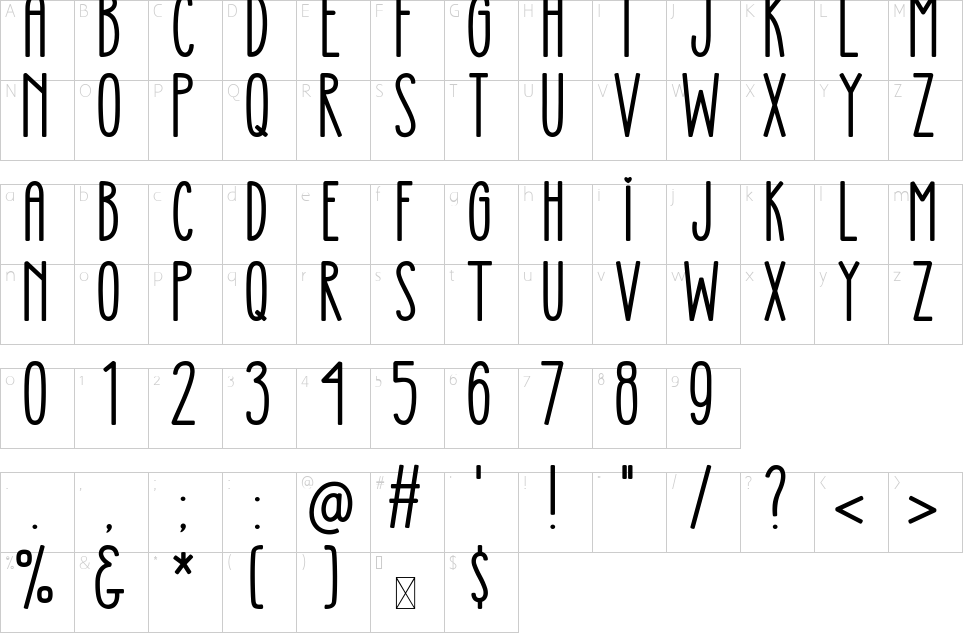
Descubra a delicadeza e o charme do Darling Kisses Font para seu próximo projeto de design. Essa elegante tipografia foi criada pelo Jimtype Studio e já recebeu 416 downloads, um número que reflete o seu valor. Com traços suaves e uma forma delicada, esta fonte se destaca como uma opção perfeita para aqueles buscando uma adição poética a seus trabalhos. Seja em sua escrita corporativa ou no design gráfico de moda, este Darling Kisses Font oferece um toque refinado e personalizado que certamente será bem-vindo. Para quem busca qualidade sem custos, essa é uma escolha inteligente para suas necessidades de design. Sua descarga pode ser feita gratuitamente a partir da categoria de fontes grátis em seu computador Windows ou Mac.